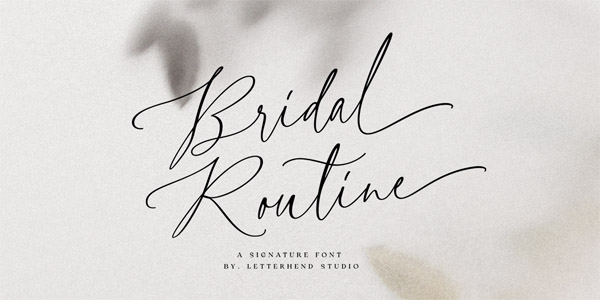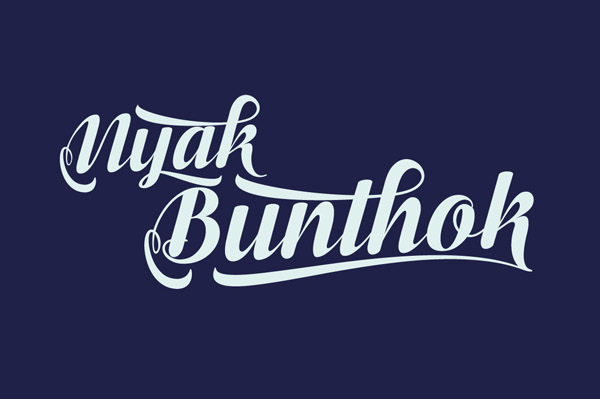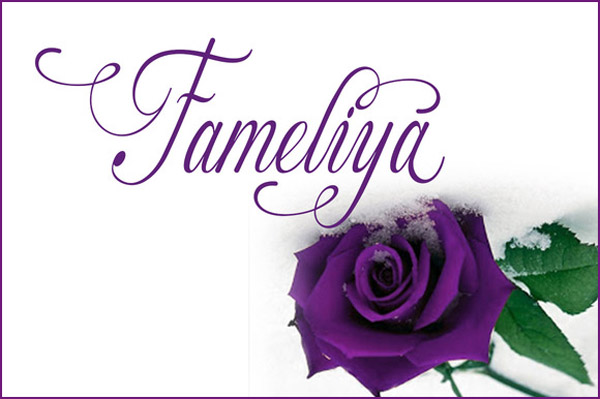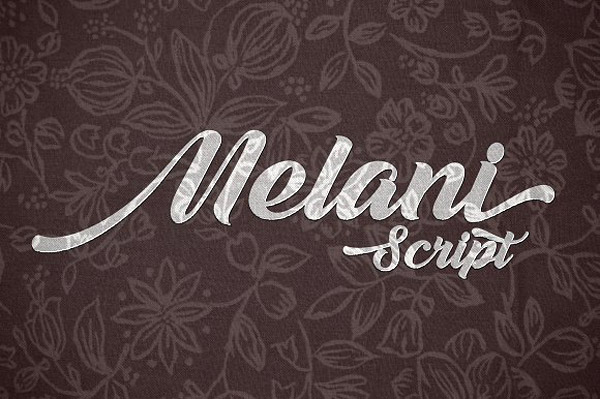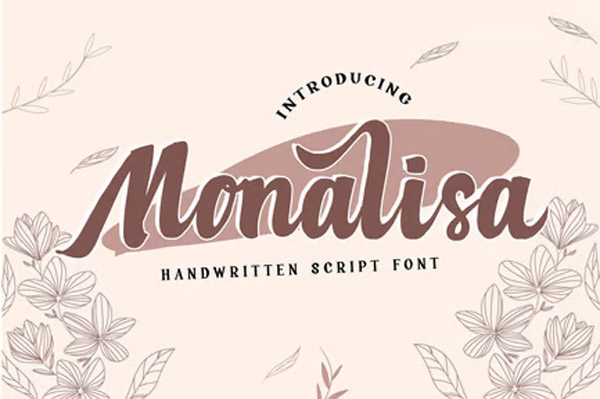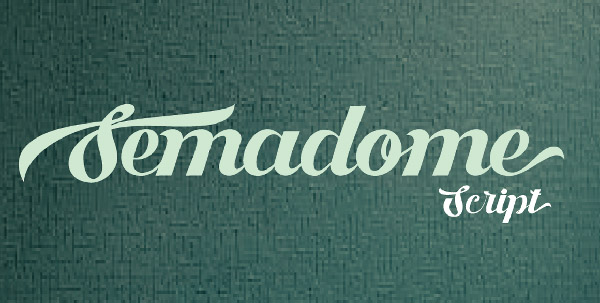
حزمة (6) خطوط إنجليزية كلاسيك ورومانس
حزمة (6) خطوط إنجليزية كلاسيك ورومانس .. حزمة منتقاة بعناية تحتوي على (6) خطوط إنجليزية كلاسيكية قديمة ذات طابع رومانسي، يمكن استخدامها في عمل البطاقات والدعوات والحفلات والمناسبات، الحزمة متاحة للتحميل المجاني الان.
حزمة (6) خطوط إنجليزية كلاسيك ورومانس
Bridal Routine – Bunthak – Fameliya
Melani Script – Monalisa Script – Semadome